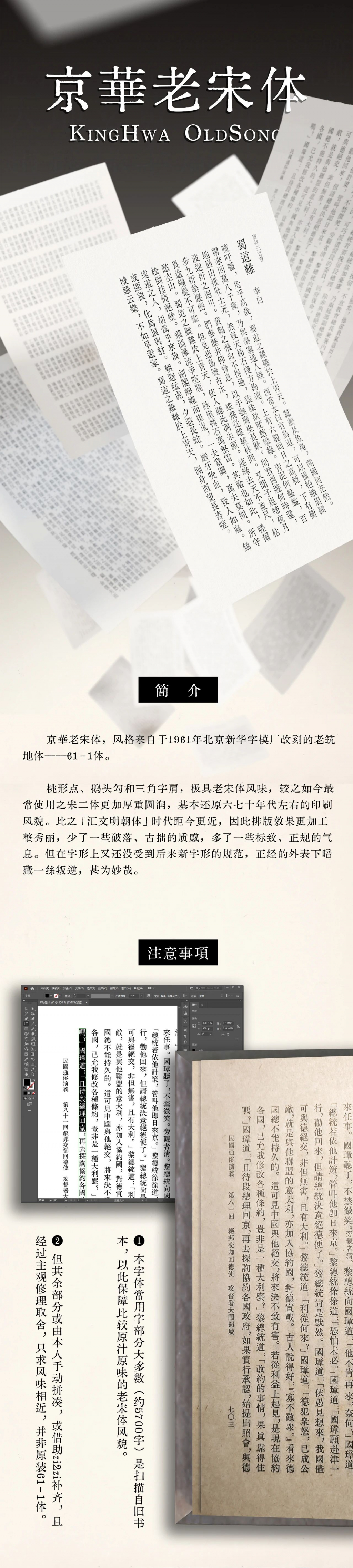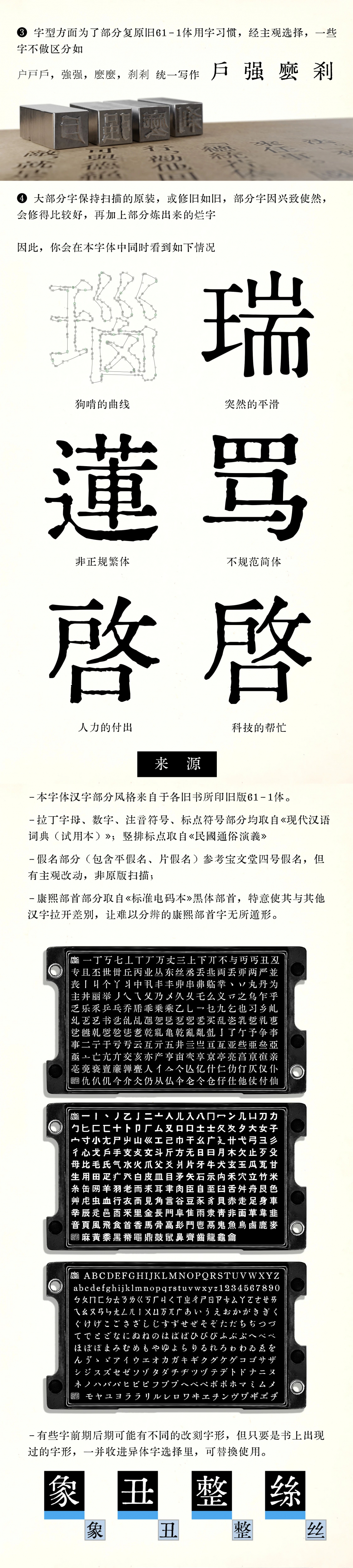
收录范围
- 统一码基础汉字区:全收录
- 统一码扩展 A 区:全收录
- 统一码扩展 B – G 区:选择部分收录
- 喃字常用字表 [2]:全收录
- 已编码二简字 [3]:全收录
后续计划(画饼
- 慢慢提高常用字部分原装 61-1 比例
- 全繁体版
- 半繁简版(仅保留第一次简化方案公布的简体字,不含类推)
提及书目
- 《汉语词典(原名:国语辞典)》商务印书馆,1962
- 《现代汉语词典(试用本)》商务印书馆,1973
- 《电报拼音化》文字改革出版社,1965
- 《韵辙常识》北京人民出版社,1978
- 《民國通俗演義》中華書局,1973
- 《日本列岛改造论》商务印书馆,1972
- 《北京新华字模厂汉文字模字体样本》,1961
- 《北京新华字模厂字目表》,1965
- 《中华人民共和国出版史料(1964-1966)13》
- 《初级中学课本 代数 第一册》人民教育出版社,1966
- 《初中代数课外习题集》上下两册 人民教育出版社,1966